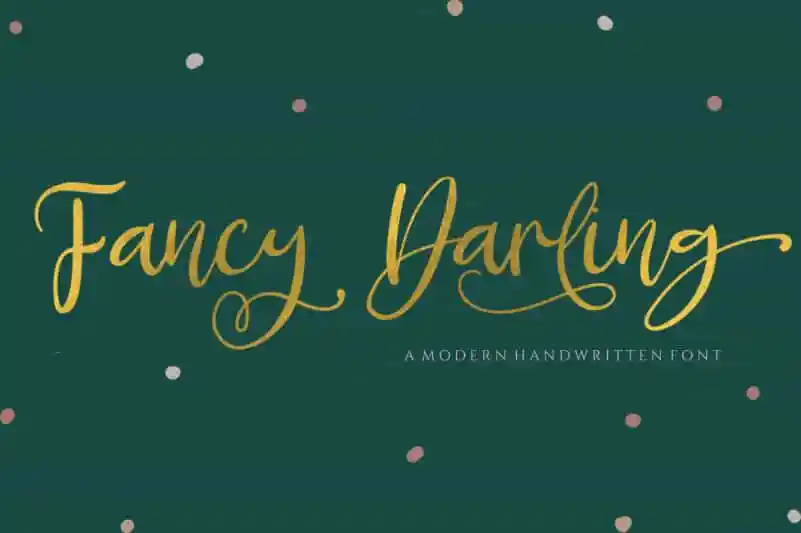
Fancy Darling Calligraphy Font – Download Grátis
Introduzimos a Fancy Darling, uma nova fonte de letra escrita à mão com fluxo elegante e inebriante. Ideal para aquelas produções que buscam exalar sofisticação e delicadeza, esta fonte script apresenta um design natural e fluido. Criada pelo designer ReyreyBlue, a Fancy Darling oferece uma experiência única de digitação, combinando elegância com perfeição manual. Seja em cartões de aniversário personalizados ou em layouts para revistas, sua presença será notável e memorable. Descubra por si mesmo o encanto desta fonte de letra script, uma verdadeira paixão para os amantes do design gráfico.